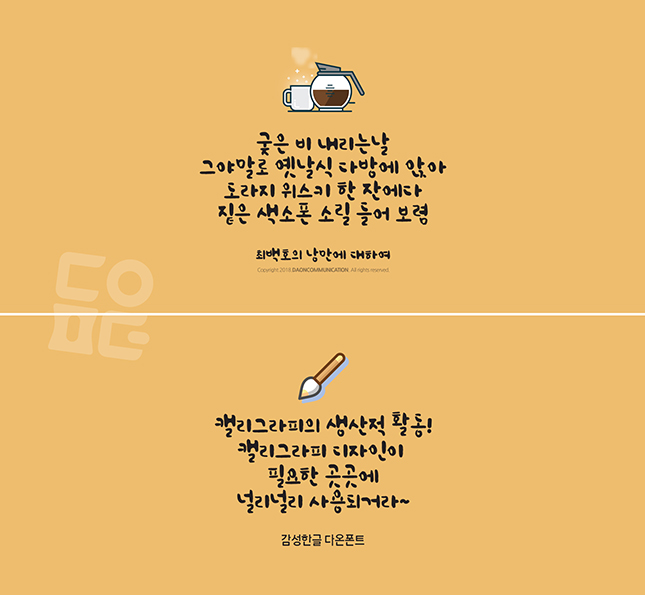
한글콘텐츠 '시골다방' 폰트가 출시되었습니다
다온폰트에서 한글콘텐츠 '시골다방' 폰트를 출시했습니다.
시골다방체는 가로정렬 가독성이 좋아 누구나 쉽게 사용할 수 있는 폰트입니다.
11,172자의 한글, 숫자, 영어까지 구성 되어 있고 타이틀디자인용 한글서체로 개발되었습니다.